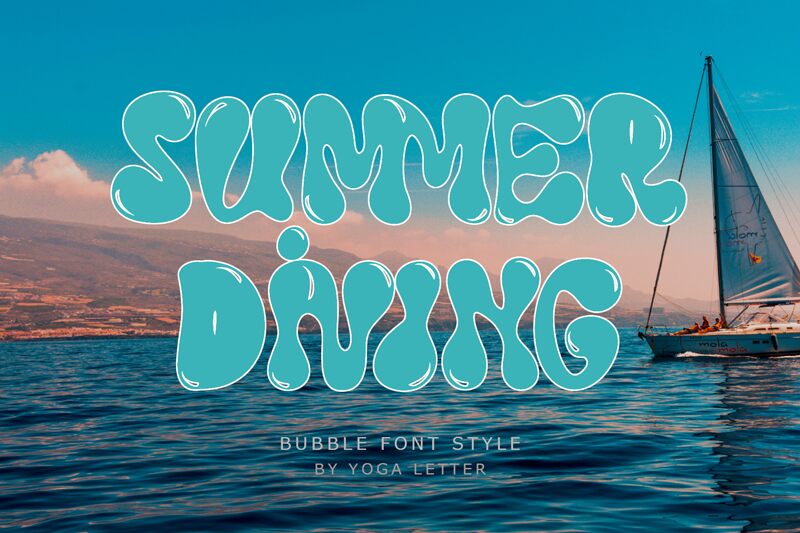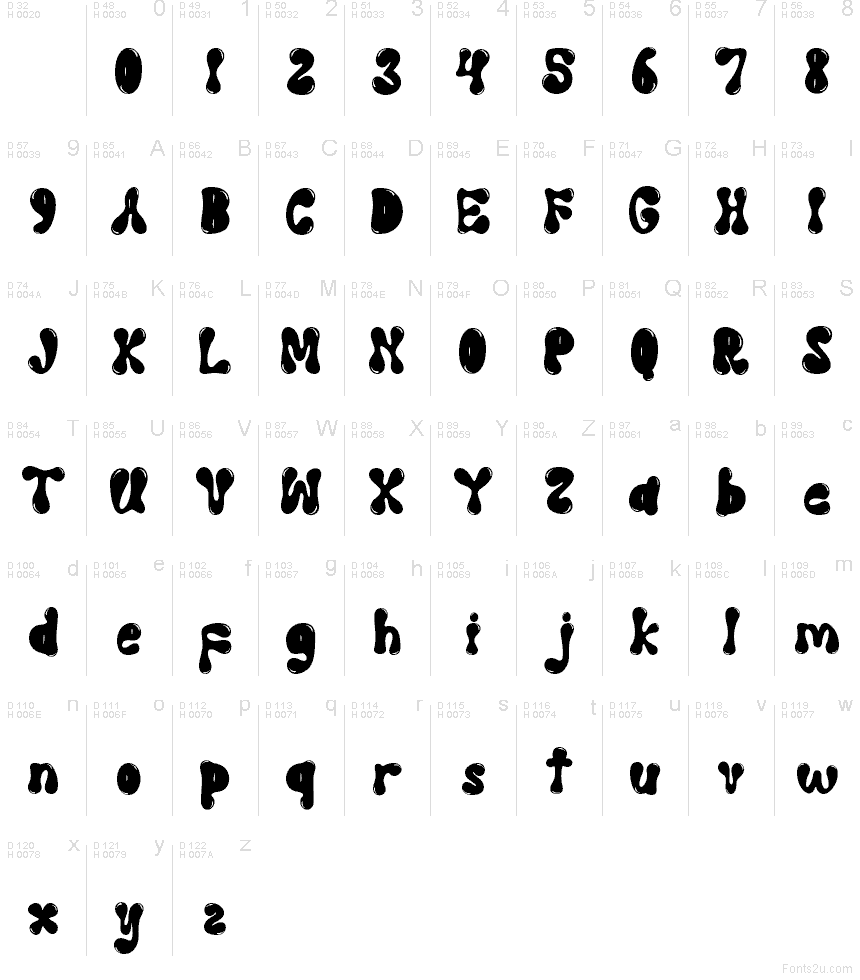
Summer Diving
Summer Diving par Yoga Letter est une police d'affichage gratuite au style groovy, caractérisée par des formes arrondies, généreuses et des courbes fluides. Son aspect évoque le dessin à la main, avec un léger effet ondulé et des virages larges qui confèrent au lettrage un rythme doux et élastique.
Summer Diving est idéale pour vos affiches estivales, invitations à des soirées plage, flyers d'événements rétro, enseignes de café ou pochettes d'album, car ses formes courbées dégagent une énergie décorative décontractée sans jamais paraître désordonnée. Cette police gratuite convient aussi parfaitement aux logos courts, aux visuels pour les réseaux sociaux et au branding saisonnier lorsque vous souhaitez que le texte s'intègre naturellement à votre design.